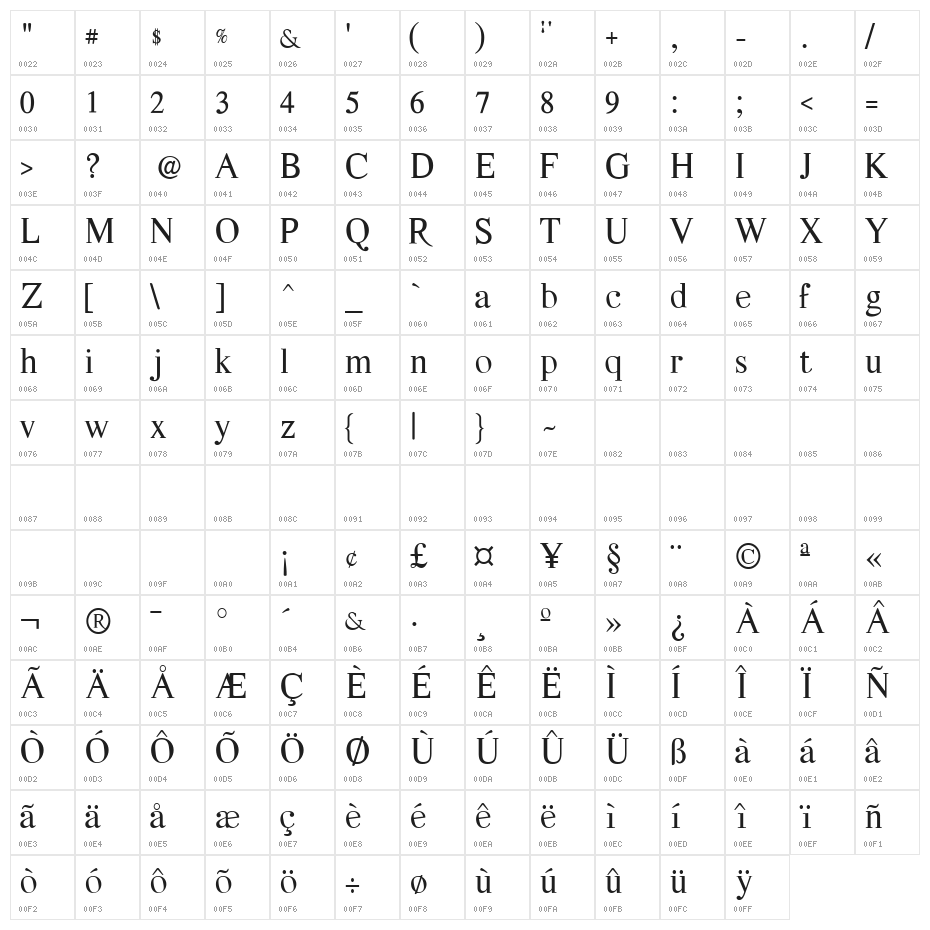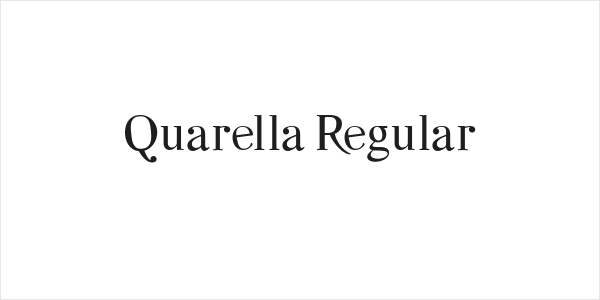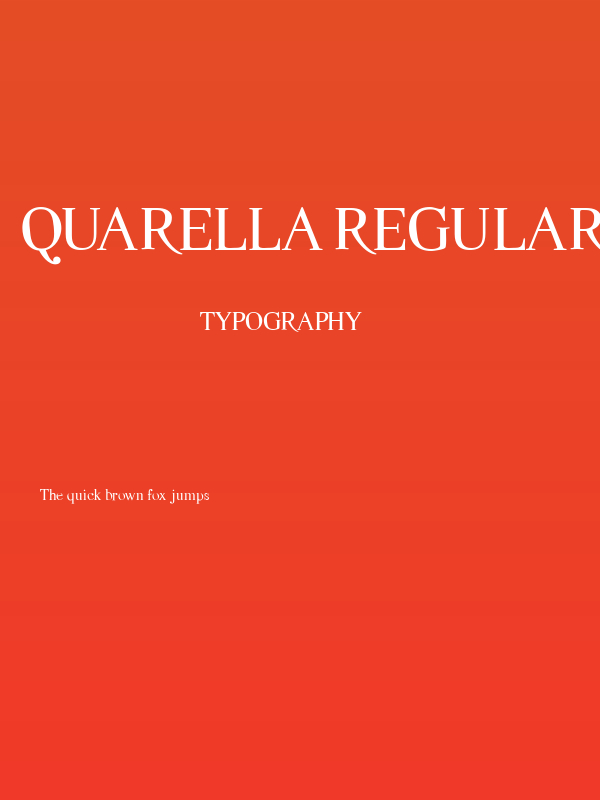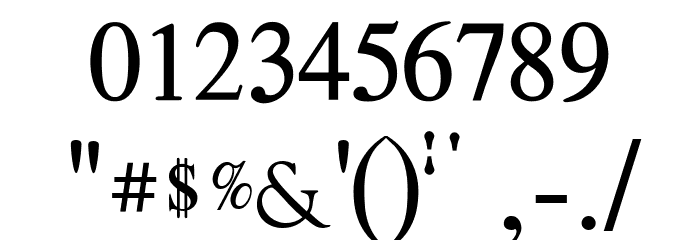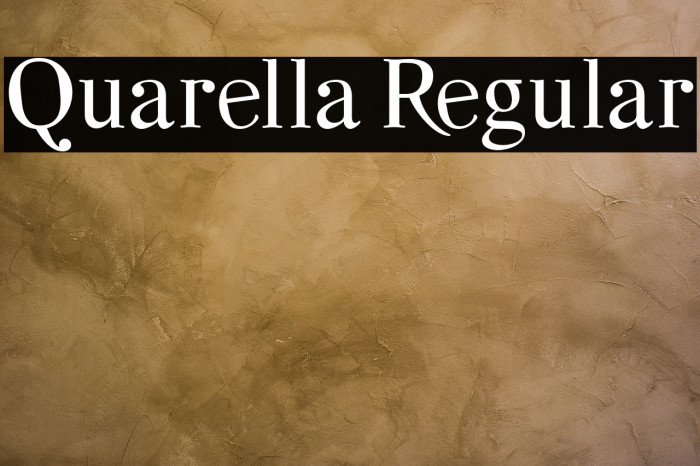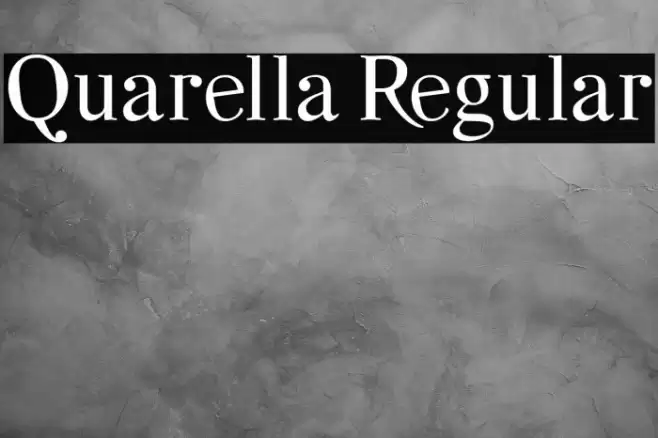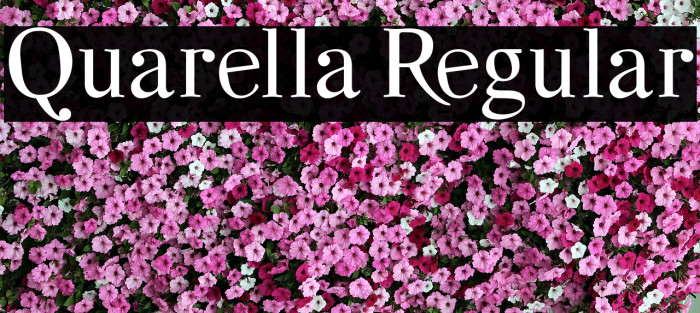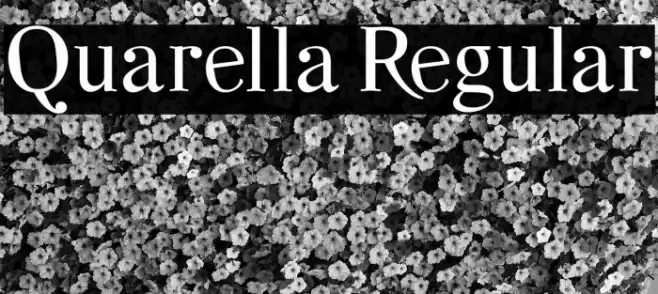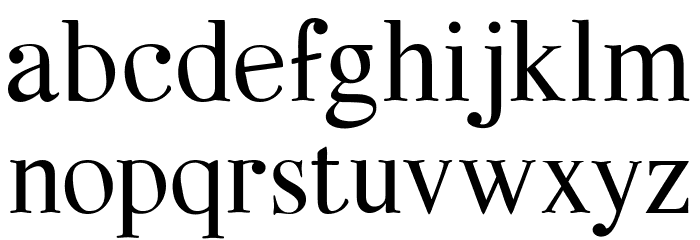
Quarella Regular Font
| Kategorien | Serif |
| Gesamtstil | Classic |
| Anwendungsfall | Headlines, Body text, Logos |
| Vorgeschlagene Projekte | Ideal for editorial design, book covers, formal invitations, and branding projects that require a touch of elegance. |